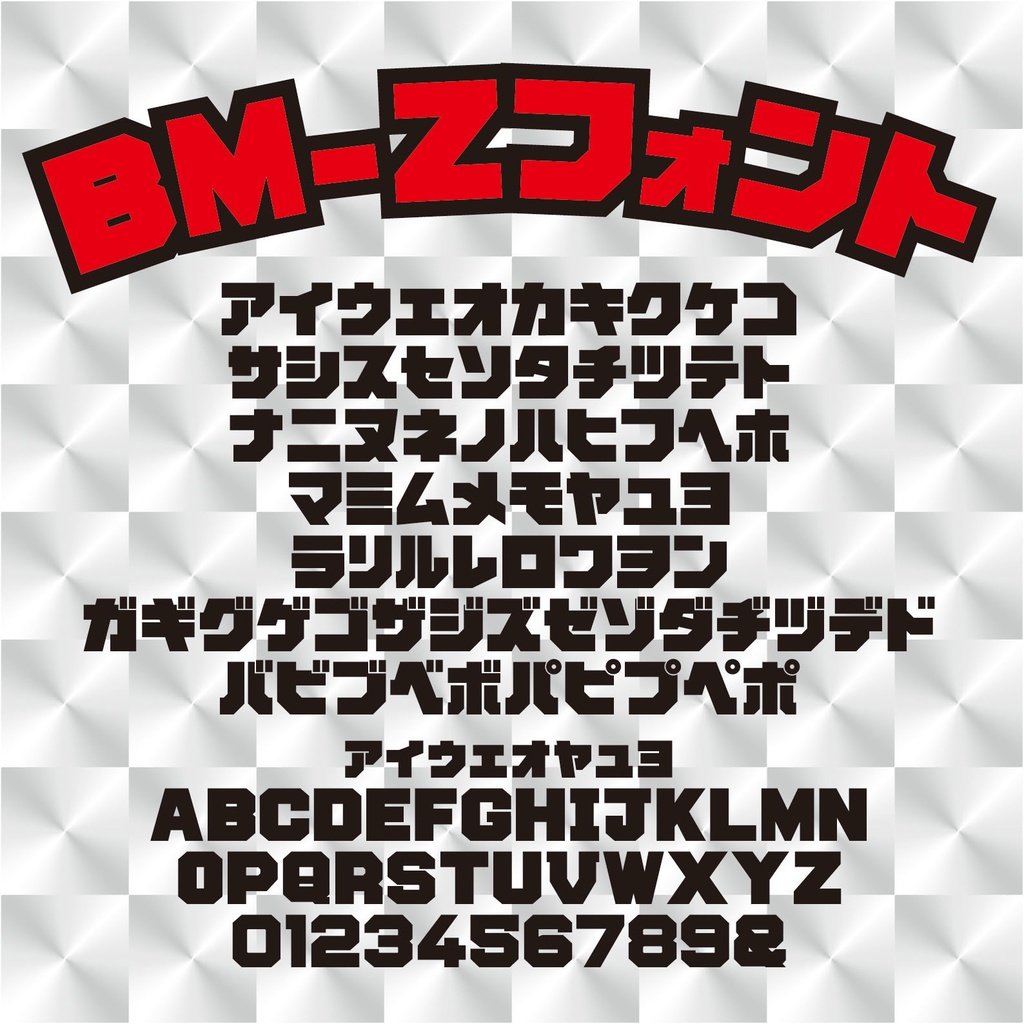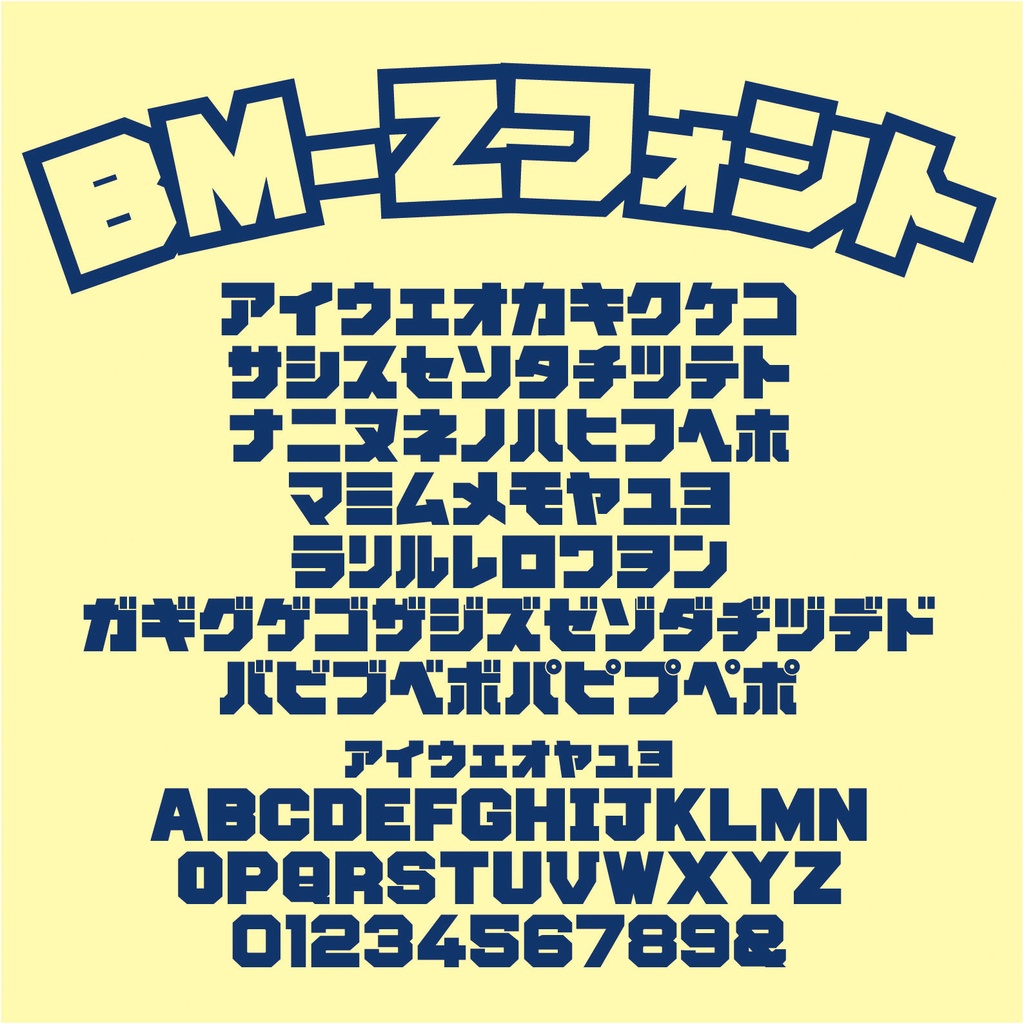
BM-Zフォント
ご覧いただきありがとうございます。 オリジナルで作成した、ビックリマンの天使ヘッド風の2バイトフォント(OpenTypeフォント)です。 イラストレーターにてパス1点1点丁寧に作成しております。 収録文字はカタカナ、アルファベット、数字のみの書体になります。 商用・個人で安心してご使用いただけるロイヤリティフリーの書体になります。文字の加工・変形もご自由にお使いください。 ■利用規約 二次配布・二次販売は禁止です。 当フォントを利用したことにより生じた損害について作成者は一切の責任を負いません。 ----------------------- 2025.12.6 更新 ・フォント名「BM-Z」に変更 2025.8.30 更新 ・アルファベットと数字を追加しました。 ・OpenTypeフォントに変更いたしました。